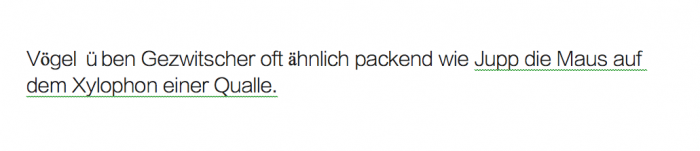
Suche ähnliche Schrift zur Lantinghei TC/SC (Extralight)
ich bin auf der Suche nach einer Schriftart di der o.g. Schriftart sehr ähnlich ist, also geradlinig, elegant & schlicht. Sie sollte auf jeden Fall "ß" & "ü,ö,ä" beinhalten.
Hier noch ein Beispiel zur Schrift:
Die Schrift ist eigentlich für chinesischen Satz, die lateinische Belegung wurde nur der Vollständigkeitshalber mit Arial oder sowas aufgefüllt. Wenn du also was ähnliches für die lateinischen Zeichen suchst guckst du vielleicht mal hier: http://www.typografie.info/3/page/Schriften/listen.html/_/statische-alternativen-zur-arial-–-neutrale-bis-sachlich-schlichte-serifenlose-r11
oder hier:
http://www.typografie.info/3/page/Schriften/listen.html/_/statische-alternativen-zur-helvetica-–-neutrale-bis-charakterstarke-serifenlose-r8
Arial kommt nicht in Frage, die ist zu dick. Ich suche eine dünne, filigrane Schrift.
zwar sehr nahe dran, aber noch nicht genau das 100%, wie ich es mir vorstelle. Trotzdem noch einmal vielen Dank für die schnelle Hilfe. Ich werde heute nach nochmal das I-net durchforsten.